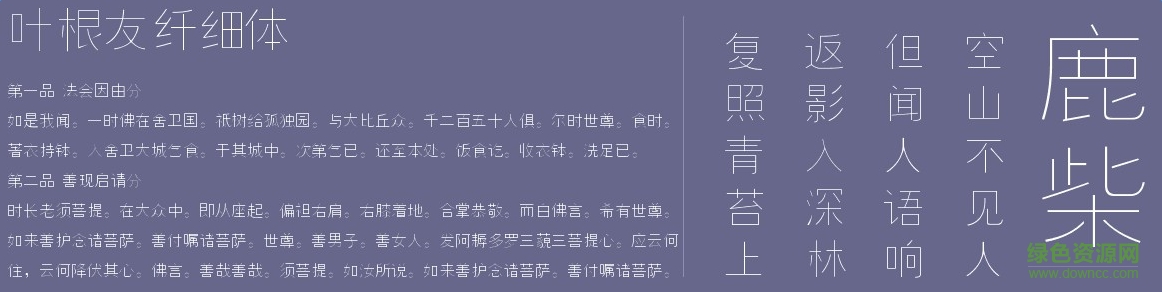
葉根友纖細(xì)體是一款由知名書法家葉根友創(chuàng)造的字體,比劃圓潤,適用于廣告、藝術(shù)設(shè)計,海報設(shè)計等方面,有需要的朋友們不要錯過了。歡迎大家來綠色資源網(wǎng)踴躍下載哦!
葉根友纖細(xì)體,一款經(jīng)典的細(xì)體風(fēng)格的字體,所有葉根友系列字體中筆畫最細(xì)的字體,適合內(nèi)文排版,手機(jī)系統(tǒng),內(nèi)嵌程序等應(yīng)用。
葉根友纖細(xì)體,用途廣泛,是葉根友先生的印刷字體,字體看起來柔美,纖細(xì),如同柳枝輕撫書頁,看起來很舒心。各位字體收藏者可以來看看。